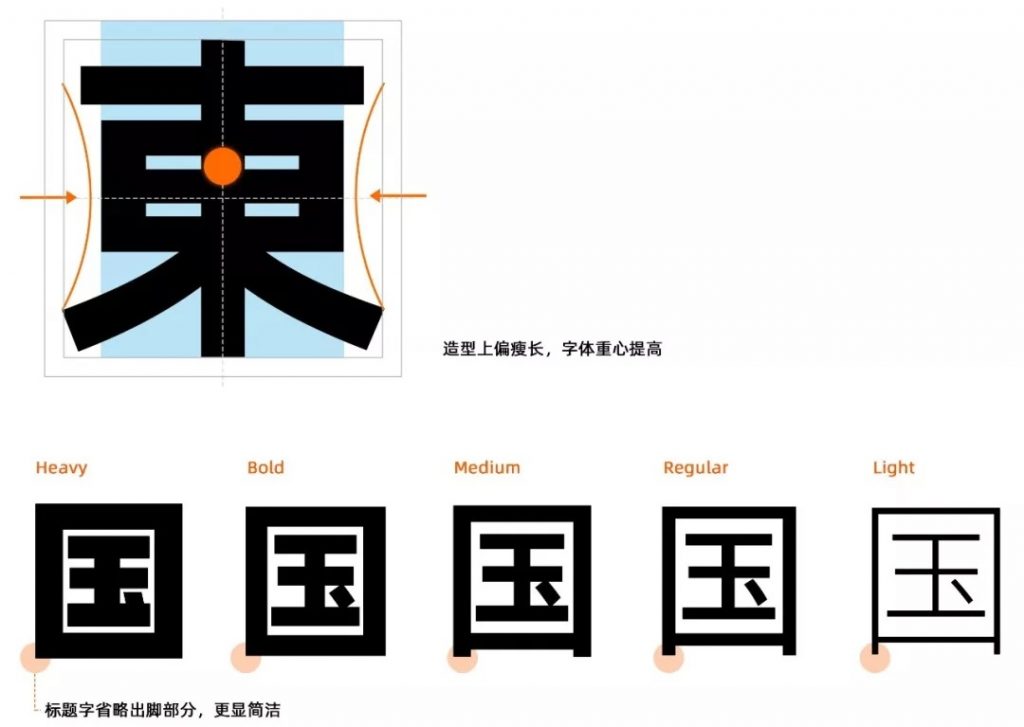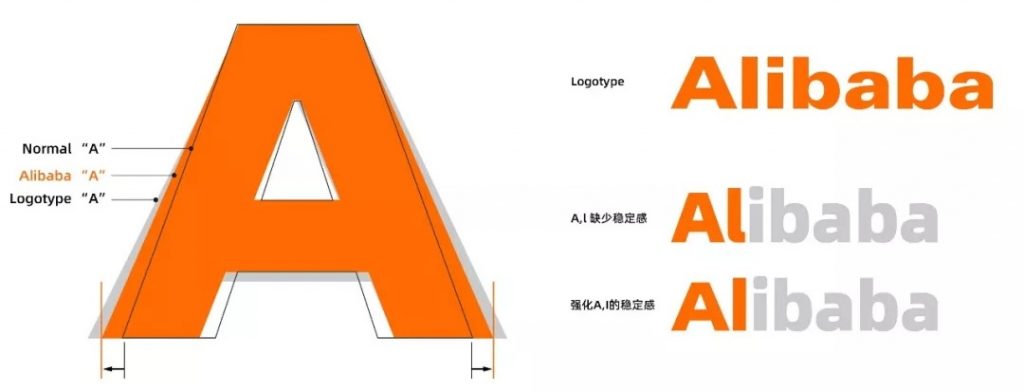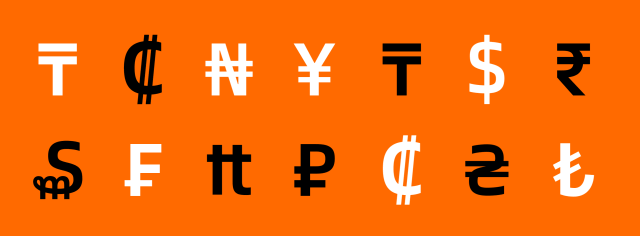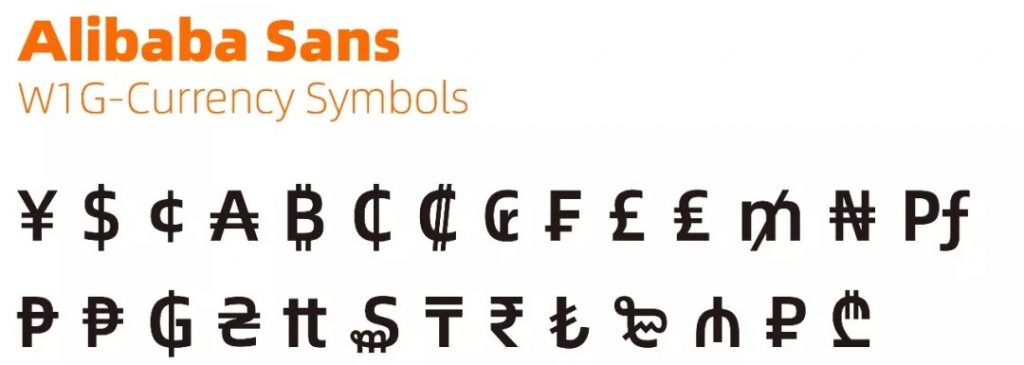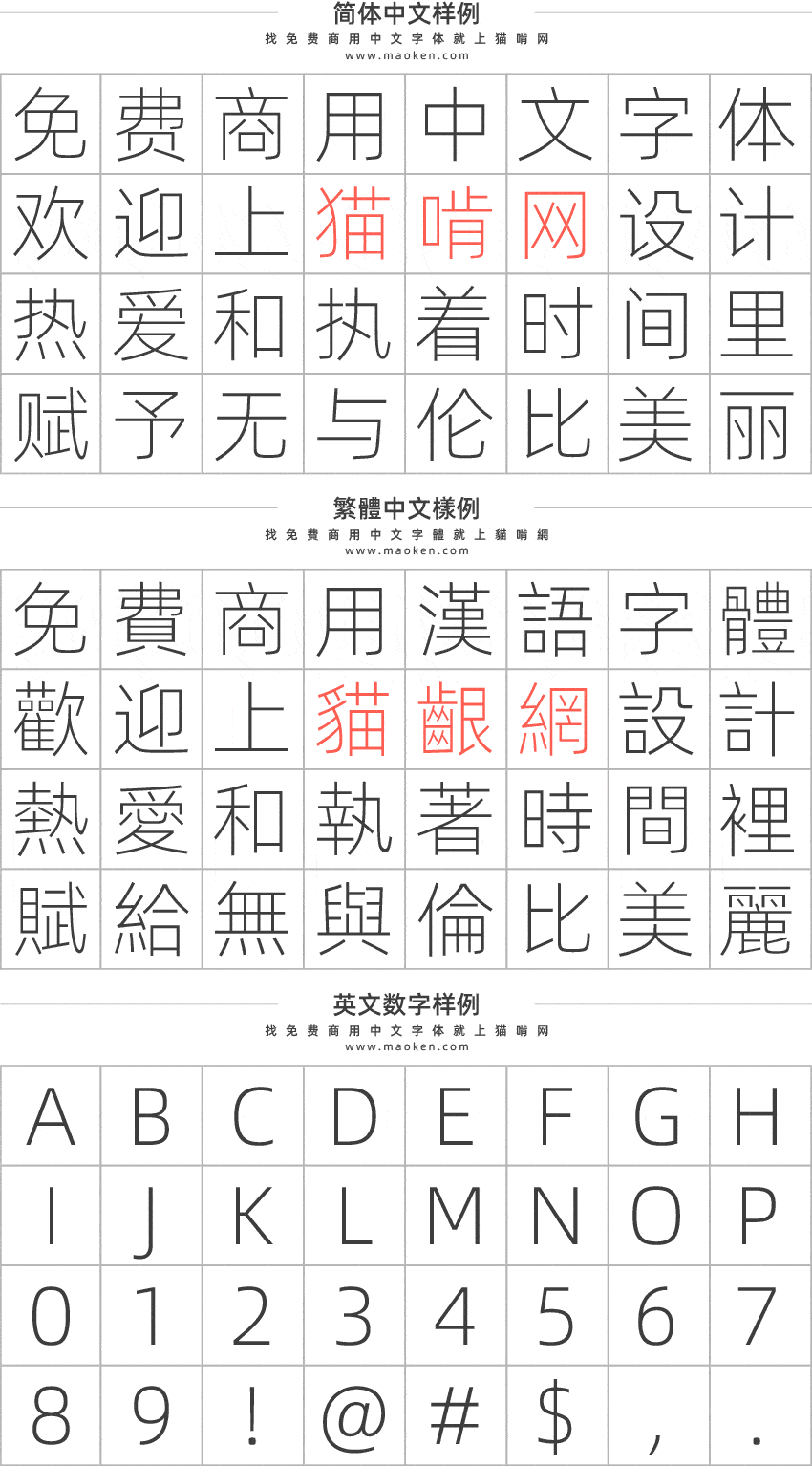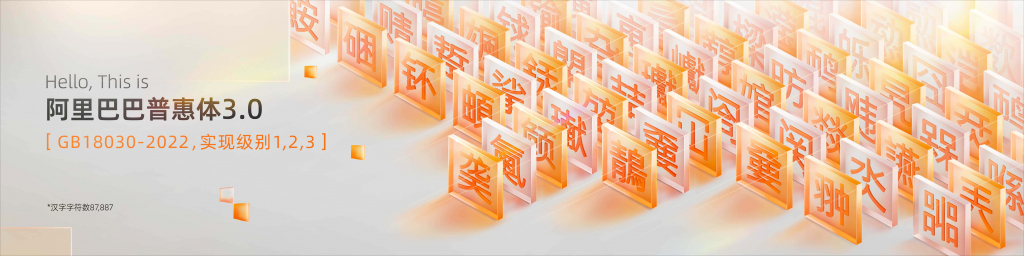
阿里巴巴普惠体:阿里出品 让天下没有难用的免费商用字体
阿里巴巴普惠体于2023年6月01日更新3.0版本
阿里巴巴普惠体是一套全球永久免费正版商用的字体家族。阿里巴巴普惠体3.0为一套符合新国家标准GB18030-2022的简体中文字符集,包含GB18030-2022强制规范三个实现级别:实现级别1+实现级别2标准规格的7字重、实现级别3标准规格的Regular 单一字重。7字重共194,460个全形汉字。包含拉丁字母、希腊字母、西里尔字母、标点符号。
【GB18030-2022 实现级别摘要】GB18030-2022标准执行方式改为三个实现级别,不再分为强制部分和推荐部分。
1. 实现级别1:用于最基本的中文信息处理和交换
实现级别1在GB18030-2022的标准中,要求在GB18030-2005强制部分的基础上去掉新标准中删除的编码部分,并加上在CJK基本平面下的新增的66个汉字共27,584汉字。任何适用的产品均应满足实现级别1的要求。
2. 实现级别2:用于促进《通用规范汉字表》的信息化应用
实现级别2包含实现级别1。此外,实现级别2还支持《通用规范汉字表》中的没有包含在实现级别1之内的编码汉字196汉字。系统软件及支撑软件,应满足实现级别2的要求。
3. 实现级别3:用于解决信息系统生僻字问题
实现级别3包含实现级别2。此外,实现级别3 还支持本文件规定的全部汉字及康熙部首部分。
用于政务服务和公共服务的产品应满足实现级别3的要求。
阿里巴巴普惠体字体介绍
中文字体多采用现代简洁的笔画,造型上偏瘦长,并将字的重心提高,以展现 20 岁阿里巴巴少年的精气神。字体笔画上也做了一些简化,如标题字省略出脚部分,更显简洁。
西文字体进行了 11 个字重、四大风格的变化演绎,以适用于多个场景的应用。在 Alibaba 单词的体现上,通过增加 A 的宽度、L 的变化等来确保字体下盘的稳定性。
数字部分,考虑到商家的应用场景,会特别注意买家的视觉体验,让它们看起来是「亲切地、好接受的」。
就连货币符号也基本囊括了当前全球大部分重要市场。
复合字:打破传统造字逻辑
由全球知名字体公司 Monotype 的字体总监小林章主导西文字体部分的设计,汉仪字库主创设计师陶一泓主导中文部分的设计,阿里巴巴普惠体的设计过程其实是一次打破传统造字逻辑的尝试。
大多数情况下,字体设计师会先从更容易形成强烈风格的西文(拉丁)文字或者中文设计着手,再进行数字和其他符号的衍生设计。
但考虑到阿里现有的业务,阿里巴巴定制官方正文字体的设计风格需要同时满足以下九个最常见的业务场景:客户端(淘宝、天猫等)、营销场景(页面、物料)、线下大屏幕、操作系统、IoT 硬件设备、建筑空间、公关传播、礼赠品、商家授权。因应这些不同的使用场景,阿里设计团队对西文、中文和数字都分别提出了不同的设计逻辑,并确定了 9 个体感关键词:动态的、多变的、年轻的、激情的、气势的、力量的、未来的、创新的、科技的。「这套字体不是单纯从某一种西文或中文字体的造型特征出发进行延展,而是以 9 个品牌体感词为切入点,将体感共鸣转换为字体造型。这才有了现在这套中西文各具特色,却又具备同一种“精气神”的复合字体。」羿光介绍。
这样的设计尝试对于两家字体设计公司来说都是前所未闻的。「比如关于数字的设计,小林章老师考虑的是数字与西文的一致性,但我们考虑的是数字会大量应用在商家的营销场景下,因此我们希望它们能兼具亲切感。」
为了确保每个字符的每个细节都精准地透传着阿里巴巴精神,并且「放大看有个性,缩小后仍然好阅读」,羿光及其团队小伙伴对每一次完稿后的成品都会进行逐字比对和抠细节,「我们会特别注意,西文字母的开口是否足够清晰,数字 5、9 等的开口是否看得更清楚,还有中文字体里笔画粘连问题。」
在他们的电脑里已经留存了密密麻麻的字体修改版,谈起抠细节的过程,羿光和他的小伙伴已是如数家珍。
阿里巴巴普惠体的未来
UCAN 大会之后,阿里巴巴普惠体就要正式面向大众了。
细心的你也许已经发现,UCAN 2019 的画面上使用的数字字体已经是阿里巴巴普惠体了。
虽然已经能够满足 172 个语种,但对于一款矢志要进行全场景覆盖的字体,阿里巴巴普惠体未来还将进行更多语种的扩充。而在未来的一年内,阿里巴巴设计团队也希望通过多方收集字体使用意见,来不断优化阿里巴巴普惠体的使用体验,欢迎大家积极提供反馈使用意见。
• 符合新国家标准GB18030-2022的简体中文字符集
• 优化了部分字体结构。
• 新增了4个字重(字体粗细)
• 新增了泰文和越南文。
• 重新以WWS规范命名字库,用以兼容同一份PPT文档在MAC和Windows系统间字形显示效果相同。
• 阿里巴巴普惠体发布